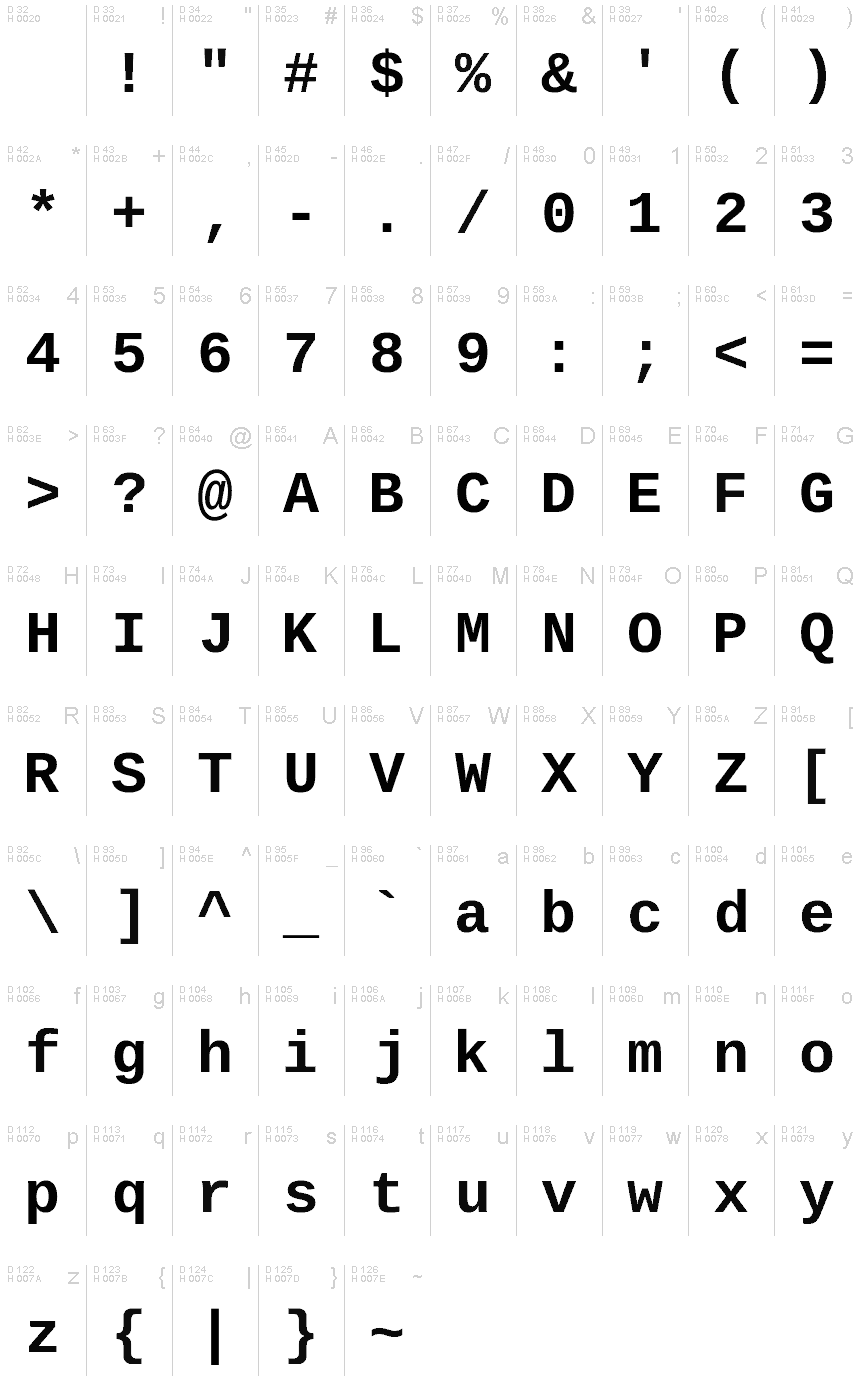
Liberation Mono Bold, di Ascender Corporation, è un carattere sans serif gratuito a spaziatura fissa che richiama lo stile sobrio e concreto dei classici font per il coding e i terminali. Le sue lettere sono ampie e solide, senza risultare troppo meccaniche, e uniscono curve generose a un ritmo squadrato per una texture visiva equilibrata e funzionale.
È quindi la scelta ideale per snippet di codice, documentazione per sviluppatori, grafica da riga di comando, mockup di interfacce e poster retro-tech, dove un font gratuito deve privilegiare l'utilità rispetto all'estetica. Funziona egregiamente anche per etichette brevi, titoli e richiami ricchi di dati, poiché la spaziatura monospazio conferisce a ogni riga un ritmo costante e preciso.